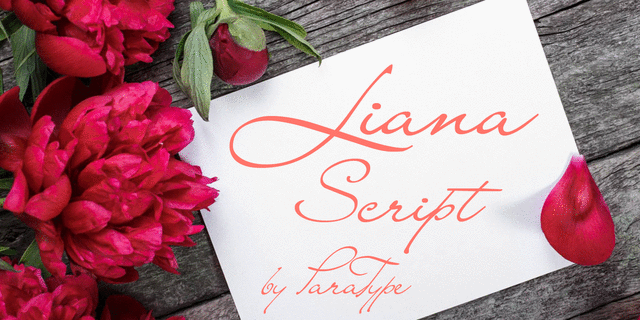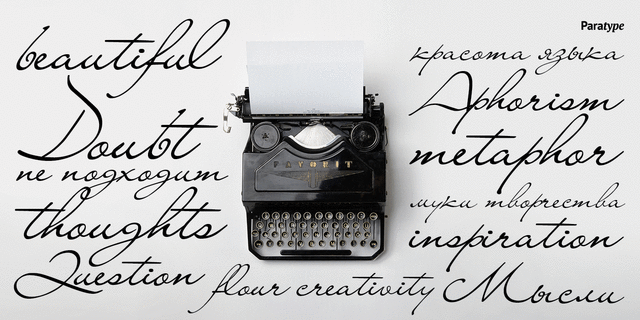
Шрифт разработан в фирме TypeMarket в 1998 (дизайнер Наталья Васильева) на основе шрифта Lainie фитрмы Soft Horizonts.
неформальный, новогодний, праздничный, радостный, свадебный, пластичный, вкусный, зеленый, свежий, модный, красивый, женственный, тонкий, воздушный, летящий, быстрый, динамичный, вдохновенный, лиричный, чувственный, эмоциональный, музыкальный, интимный, поэтичный, артистичный, элегантный, весенний, романтичный, страстный, счастливый, творческий, прелестный, симпатичный, стремительный, проворный, бегущий, растительный, аккуратный, размашистый
цветы, подарки, торт, праздник, конфеты, десерт, кондитерская, сладости, танец, парикмахерская, Новый Год, диета, музыка, косметика, кафе, гигиена, чистота, булочная, любовь, стихи, поэзия, лирика, вино, балет, весна, украшение, романтика, платье, одежда, Christmas, море, красота, инстаграм, мода, парфюмерия Стилистика: